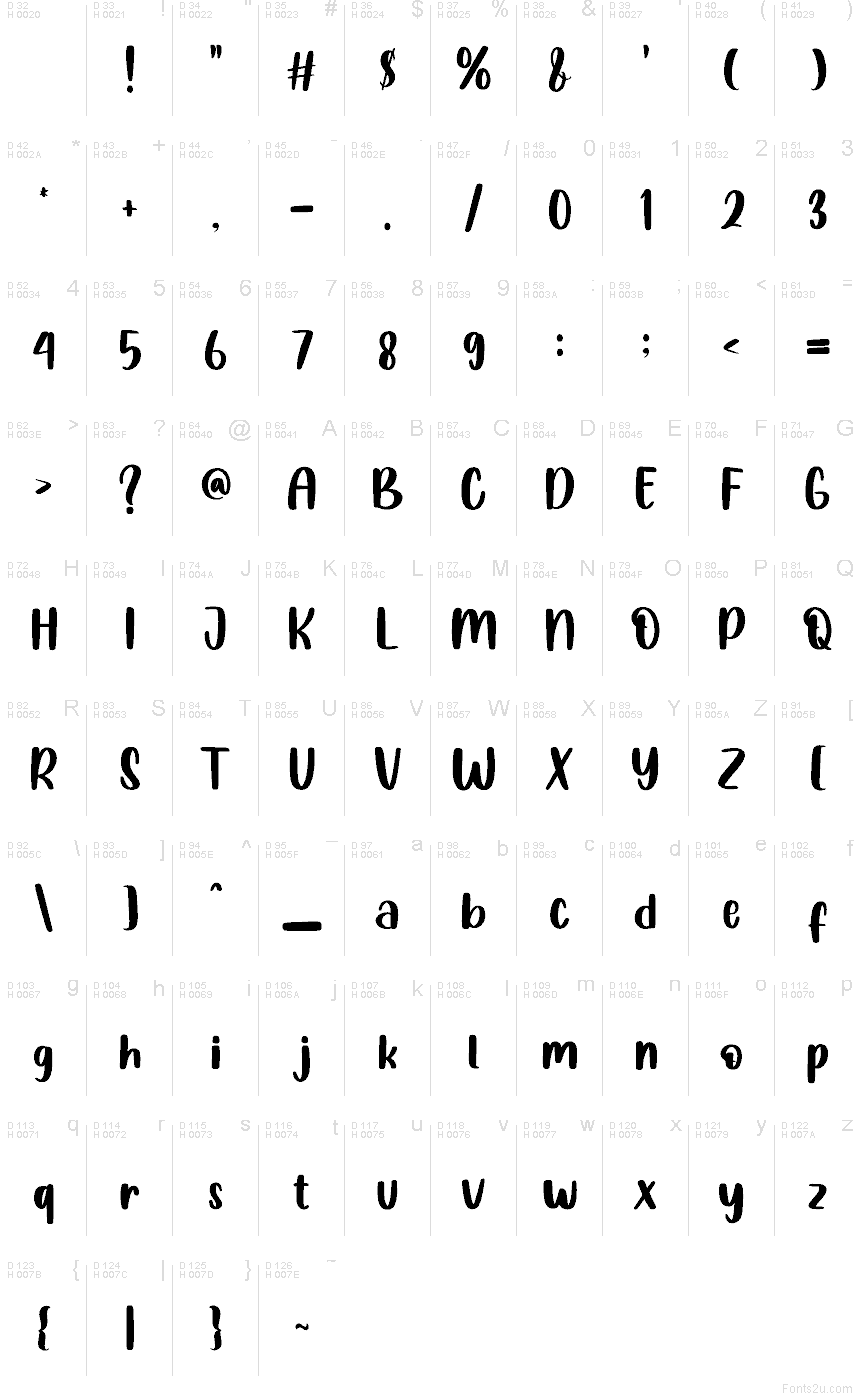
Childer ze studia Rantautype Studio je bezplatné komiksové display písmo s vysokými, úzkými a uvolněně kreslenými literami, měkkými, oblými křivkami a sympatickou nepravidelností. Zaoblené tahy mění svou tloušťku znak od znaku a nestejná výška dodává abecedě živou, rukodělnou siluetu, která zůstává snadno čitelná.
Obálky dětských knih představují přirozené prostředí pro jeho hravou rozpustilost. Protažené proporce a lehce asymetrické křivky se skvěle hodí také na obaly pochutin, párty plakáty či titulní karty her, kde text přirozeně splyne s papírovou koláží, místo aby působil jen jako neutrální sazba.